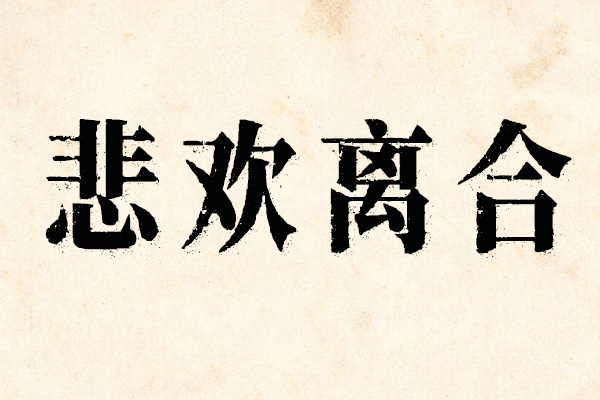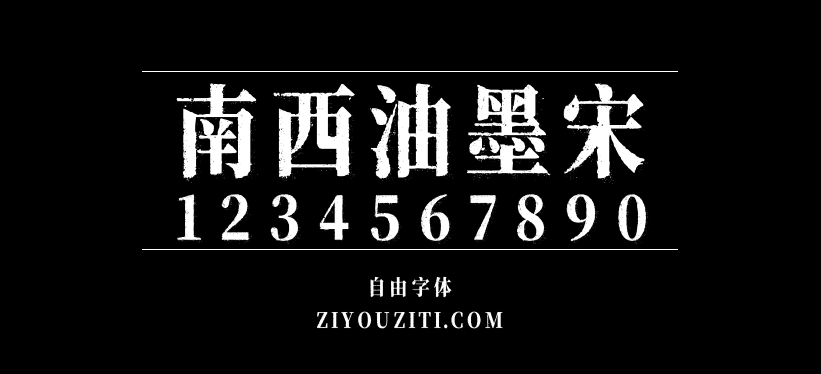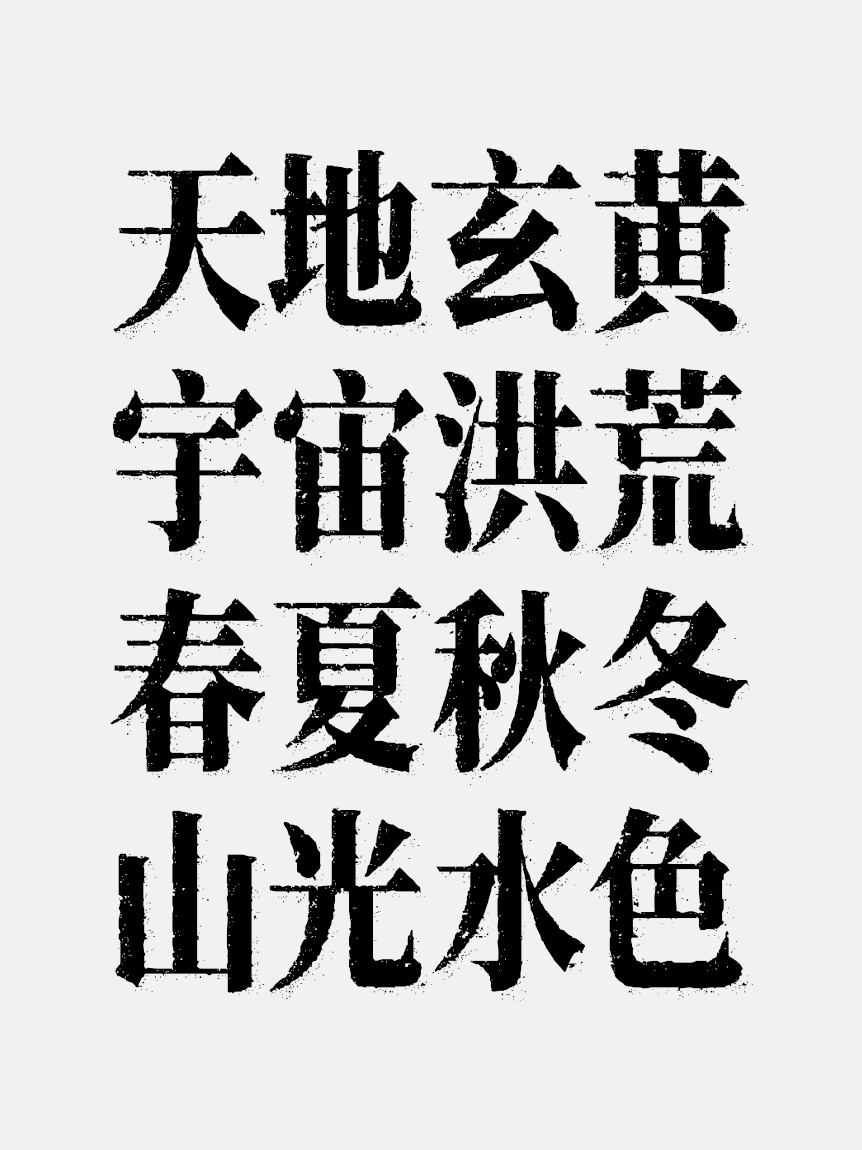
南西油墨宋
南西油墨宋的作者是公众号松陵南西,作者使用PS调的油墨做旧效果,然后导出重新封装成字体,字数简体标准6763字,适合在大字场合使用,不适合小字阅读(不容易看到效果)。作者松陵南西之前还推出过一款免费商用宋体字:南西初夏宋。
作为一款适配性极强的标题向字体,南西油墨宋非常适合复古风、国潮风、工业风海报的主标题,也能为书籍封面、文创周边、复古包装增添独特的质感细节,短视频封面、公众号头图等新媒体场景中,它也能快速营造出个性鲜明的复古调性。 南西油墨宋基于思源宋体进行二次创作,使用OFL协议授权,可以免费商用,个人非商业与商业使用均无版权限制,无需额外申请授权,是设计师打造复古质感作品的高效选择。